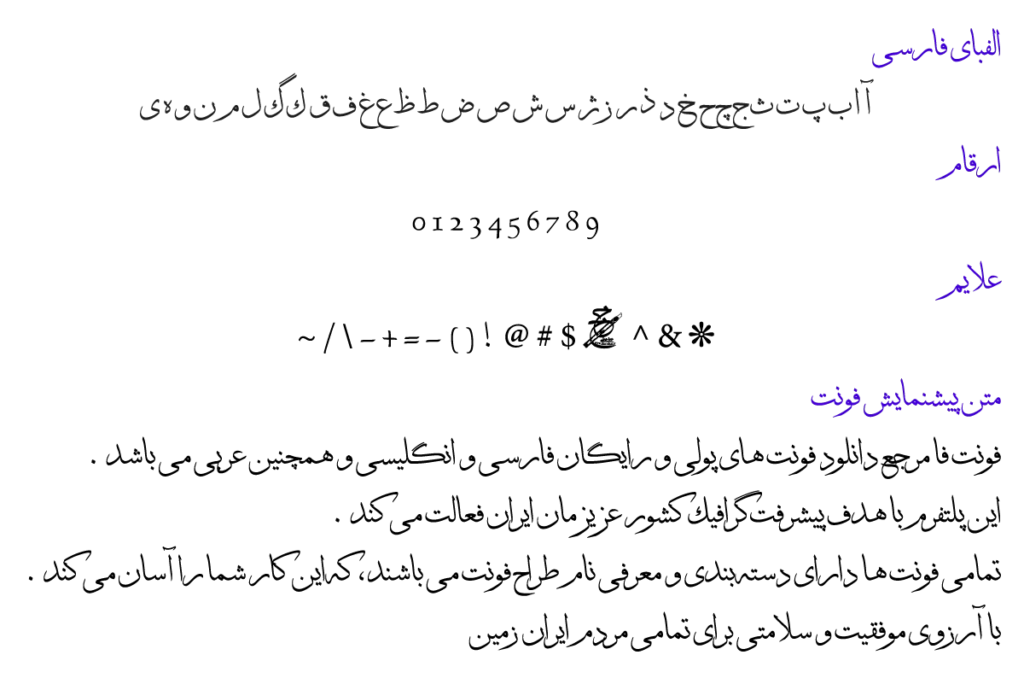
فونت فارسی ثلث – A Thuluth
نوع فونت: فونت خوشنویسی
توضیحات و معرفی فونت ثلث
فونت فارسی ثلث ( A Thuluth ) از مجموعه فونت های آزاد می باشد، و نیز نوع فونت خوشنویسی می باشد.
و نیز فونت در یک وزن معمولی است.
در تصویر زیر میتوانید دموی این تایپ فیس زیبا را با شعر زیبای وطنم مشاهده کنید.